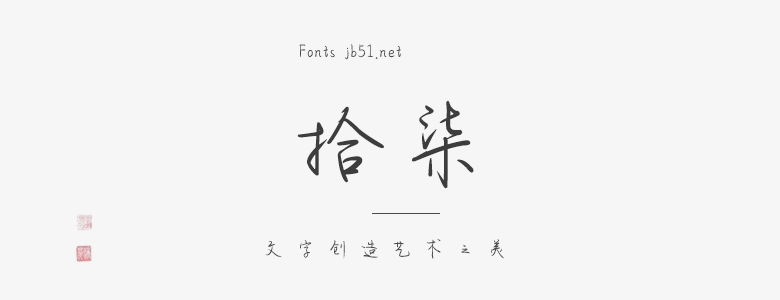
“拾柒”是一款極具個性與藝術(shù)性的字體,以其獨特的線條和設(shè)計元素,完美詮釋了現(xiàn)代設(shè)計與歷史傳承的結(jié)合。這款字體設(shè)計靈感源于中國古老的書法藝術(shù),字形結(jié)構(gòu)簡潔明了,線條流暢,視覺效果突出。同時,設(shè)計師巧妙地將傳統(tǒng)元素與現(xiàn)代審美觀念相結(jié)合,形成了一種別具一格的現(xiàn)代藝術(shù)字體。 “拾柒”字體的筆畫設(shè)計考究,粗細(xì)適中,視覺效果平衡和諧。字體中的數(shù)字和字母造型別致,既保留了原有的識別性,又在設(shè)計中融入了創(chuàng)新元素。字體的斜體設(shè)計更是引人注目,不僅增加了視覺沖擊力,還為整體設(shè)計增添了一絲時尚感。 此外,“拾柒”字體適合多種應(yīng)用場景。無論是用于標(biāo)題、廣告牌還是書籍、雜志等印刷品,都能夠以其強(qiáng)烈的視覺吸引力和獨特的藝術(shù)風(fēng)格吸引讀者的眼球。同時,這款字體的設(shè)計也為其所應(yīng)用的環(huán)境增添了一份獨特的藝術(shù)氣息。 總的來說,“拾柒”字體是一款融合傳統(tǒng)與現(xiàn)代元素、充滿藝術(shù)感和視覺沖擊力的字體。無論是在設(shè)計還是應(yīng)用方面,都展現(xiàn)出了卓越的品質(zhì)和獨特魅力,為設(shè)計師提供了一個全新的、富有創(chuàng)意的選擇。